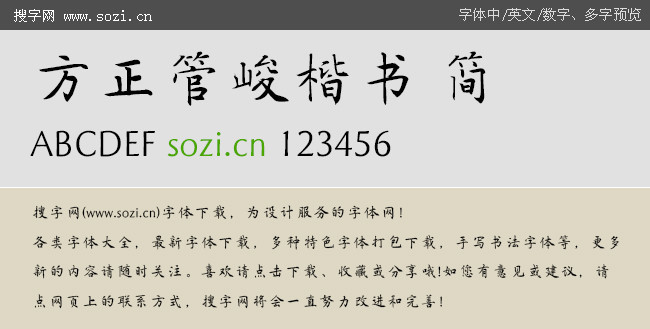
方正管峻楷書(shū)-簡(jiǎn)
搜字網(wǎng)提供一款方正管峻楷書(shū)簡(jiǎn)中文字體下載,管峻楷書(shū)由當(dāng)代書(shū)法家管峻先生創(chuàng)作。這款字體用筆細(xì)勁又多輕重對(duì)比,輕巧自然,結(jié)體以褚遂良書(shū)法為本,參以己意自成一家,工穩(wěn)清麗。其風(fēng)格秀美空靈,適用于文化類(lèi)的宣傳設(shè)計(jì),以及商業(yè)類(lèi)品牌的廣告和產(chǎn)品包裝設(shè)計(jì)。